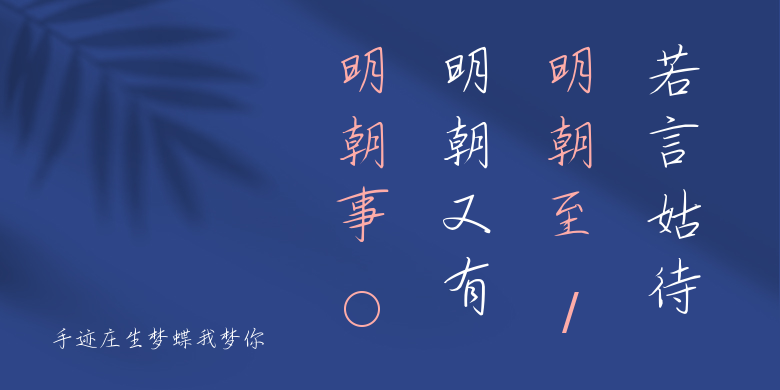
手迹庄生梦蝶我梦你
手迹庄生梦蝶我梦你,这款字体结构工整、笔画清晰,兼顾美观与易读性,适用于标题、正文、海报、包装、LOGO 等多种场景。字形优雅稳定,风格百搭耐看,适配日常排版与创意设计,让文字呈现更舒适、更具质感。手迹庄生梦蝶我梦你一笔一画,皆是细节,以均衡的比例、流畅的线条打造舒适视觉体验,字形端正大气,风格简约现代。无论是商业设计、品牌宣传还是日常排版,都能轻松驾驭,让文字更有格调与力量。手迹庄生梦蝶我梦你字体下载。